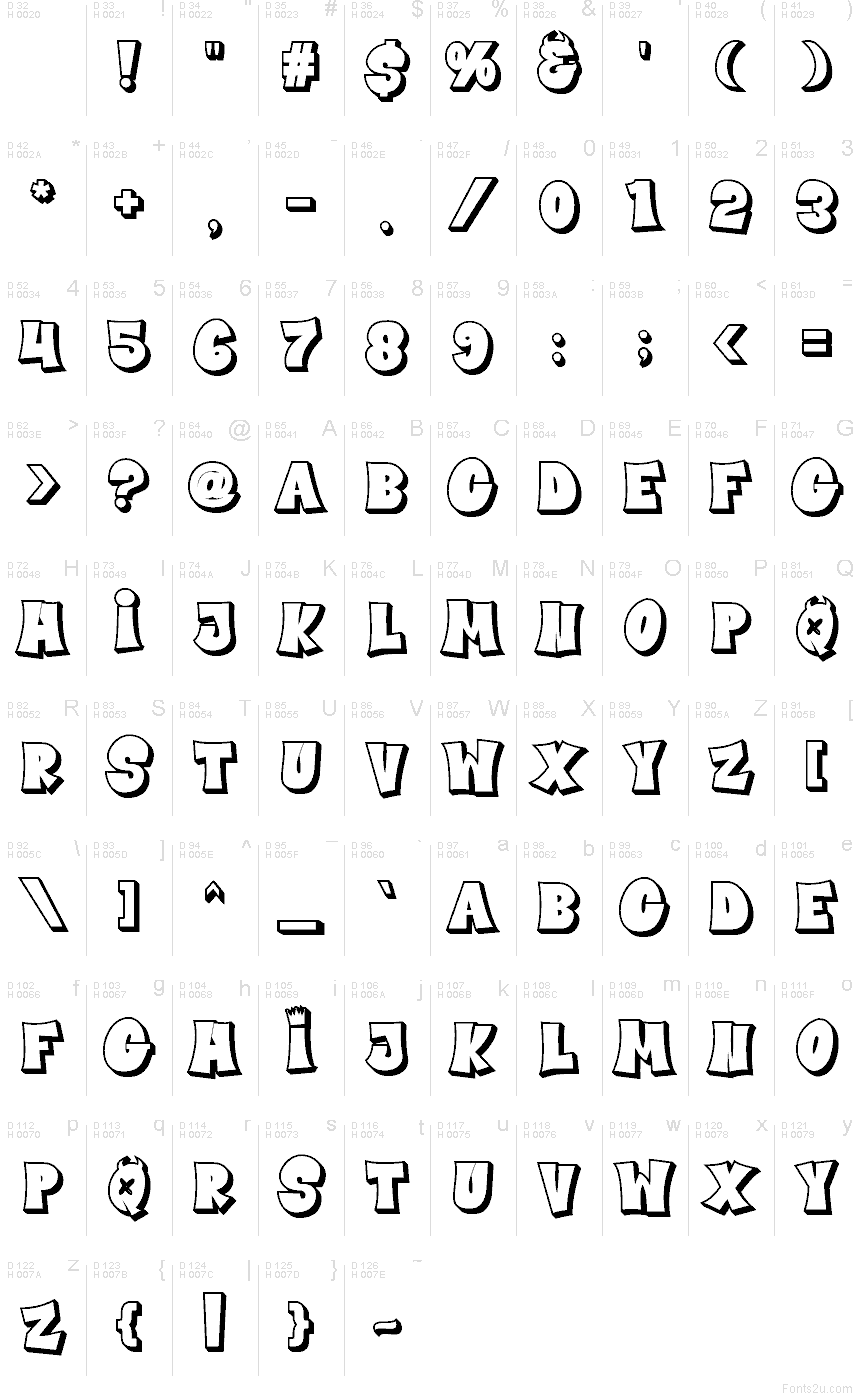
King Jack Style Shadow di Cikareotype Studio è un font display 3D in stile cartoon gratuito, con grandi lettere maiuscole e corpose che ricordano un tratto disegnato a mano. I caratteri evocano un'attitudine giocosa da fumetto, grazie a forme gonfie, contorni spessi e una netta ombra laterale che trasforma ogni parola in una sorta di piccolo ritaglio di carta.
È ideale per titoli di locandine, volantini per eventi per bambini, packaging di snack, interfacce di gioco e titoli per YouTube, dove le parole brevi necessitano di una voce vivace e d'impatto. Essendo un font gratuito, è perfetto per titoli, monogrammi e targhette d'effetto, poiché la sua ombra profonda dona anche alle iniziali più semplici un immediato senso di dinamismo.